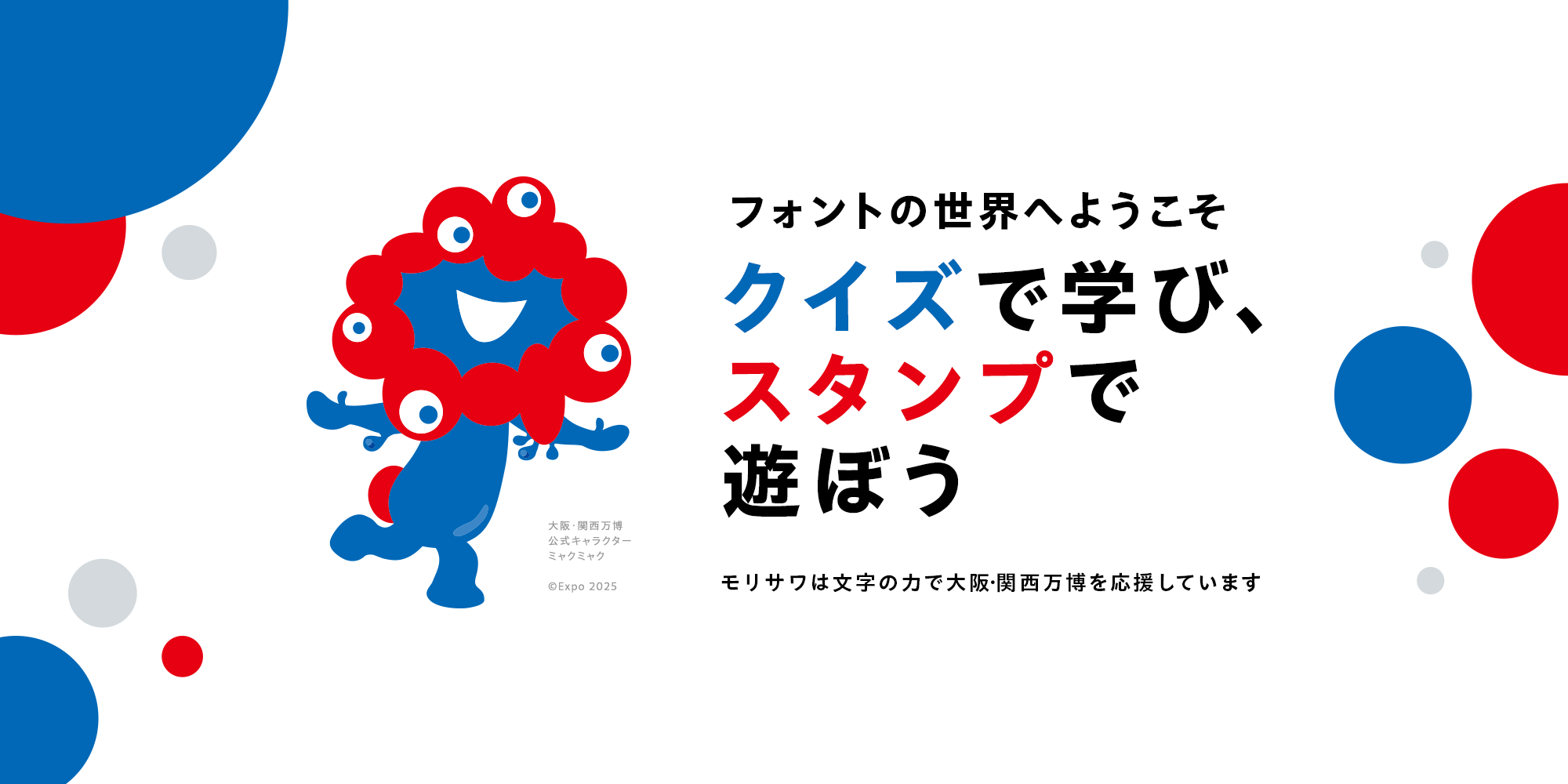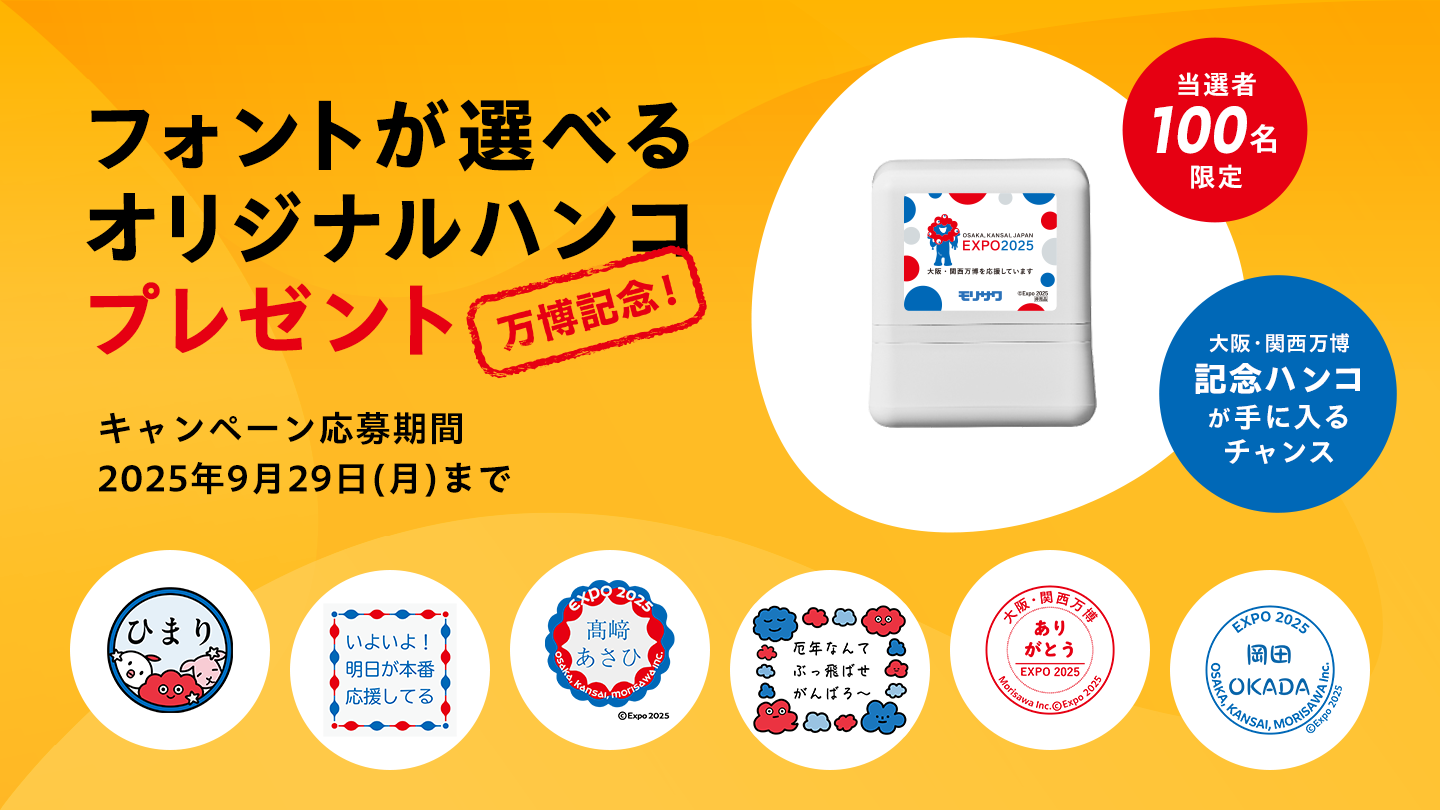
QuizKnock×モリサワのフォントクイズを大阪・関西万博特設サイトにて公開!全問正解でフォントマスターを目指そう
株式会社モリサワ(代表取締役社長:森澤彰彦 本社:大阪市浪速区敷津東2-6-25 Tel:06-6649-2151 代表、以下モリサワ)は、2025年日本国際博覧会(以下、大阪・関西万博)の「大阪・関西万博PRブロンズパートナー」として協賛していることを記念し開設した大阪・関西万博特設サイトにおいて、株式会社baton(代表取締役:衣川洋佑 東京都品川区)が運営するQuizKnockとのコラボレーションによるクイズページを新たに公開しました。
今回公開したクイズページは、「QuizKnockのフォント魅力発見! 目指せ全問正解!みんなで挑戦しよう!」と題し、フォントや文字にまつわるクイズを楽しむことができます。Webサイトや本、新聞や雑誌の記事、動画の字幕、案内標識など日常のさまざまな場面でフォントを見たり使ったりしていると思います。そんなフォントの特徴や使い分けについて、クイズ王 伊沢拓司氏が率いる知的エンタメ集団「QuizKnock」が制作したクイズを通して、楽しく学べる内容です。クイズは全部で10問、正答率によって、「フォントマスター」「フォント上級者」などにレベル分けされる仕組みになっています。楽しみながらフォントをマスターし、全問正解に挑戦してみてください。明日からフォントの見方や選び方が変わるかもしれません。
また、モリサワの大阪・関西万博特設サイトは、「フォントの世界へようこそ クイズで学び、スタンプで遊ぼう」と題して、文字の力で大阪・関西万博を盛り上げる、さまざまなコンテンツを掲載しています。フォントを選んで作れる!「フォント de スタンプ」では、大阪・関西万博モチーフのデザインを含むフレーム(台紙)とモリサワのフォントを使って、ご自身の好きな言葉やお名前を入力したオリジナルデジタルスタンプ(スタンプ形式のデジタル画像)を作成、ダウンロードすることができます。ダウンロードしたデジタルスタンプは、電子印鑑として使うのはもちろん、SNSのアイコンや写真、メッセージカードに加工するなど自由にご利用いただくことができます。クイズに登場する一部のフォントも選択することができますので、ぜひこの機会に、フォントを変えることで言葉の印象が変わる楽しさを体験してみてください。
また、作成したデジタルスタンプが、本物のハンコになって届く「万博記念!フォントが選べるオリジナルハンコプレゼント」キャンペーンも実施中です。ハンコのハンドル部分は、大阪・関西万博の公式キャラクターミャクミャクのデザインとなっており、世界に一つだけのオリジナル万博グッズになるかもしれません。
モリサワと大阪・関西万博について
モリサワは「大阪・関西万博PRブロンズパートナー」として協賛し、大阪・関西万博の会場サインやアプリなどで使用するための各種フォントも提供しています。また、「大阪ヘルスケアパビリオン Nest for Reborn」のサポーターとして、展示ディスプレイや平面サインなどで使用されるフォントを提供しているほか、その他のパビリオンでも各種フォントを採用いただいています。
モリサワのUDフォントについて
モリサワのUDフォントは、「文字のかたちがわかりやすいこと」「文章が読みやすいこと」「読み間違えにくいこと」をコンセプトに開発されています。具体的には、濁点や半濁点を大きくして、区別をつけやすくしているほか、シルエットの似た文字を判別しやすくするために、はなれを明確にするなどの工夫をしています。第三者機関と共同で可視性・可読性に関する比較研究報告も実施しています。